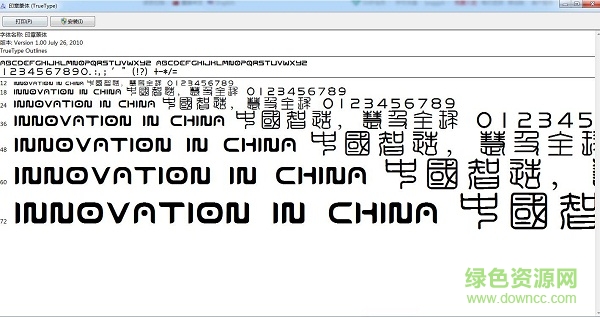
方圓印章篆體
方圓印章篆體字體是一款古典文雅的正文字體,結(jié)構(gòu)規(guī)范嚴(yán)謹(jǐn),行筆圓轉(zhuǎn),該字體藝術(shù)欣賞性強(qiáng),日常不太常見(jiàn),可以用于與傳統(tǒng)文化相關(guān)的宣傳海報(bào)設(shè)計(jì)上!
篆體分類
【大篆】:指金文、籀文、六國(guó)文字,它們保存著古代象形文字的明顯特點(diǎn);
【小篆】:也稱“秦篆”,其特點(diǎn)是形體勻逼齊整、字體較籀文容易書寫。